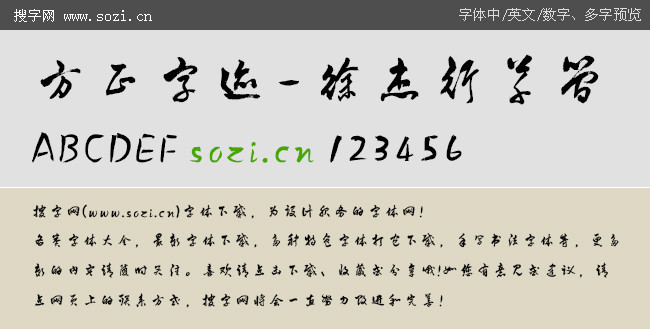
方正字跡-徐杰行草簡
搜字網(wǎng)提供一款方正字跡-徐杰行草簡中文字體下載,方正字跡-徐杰行草字體輕舞飛揚(yáng),而且連貫特殊,能夠適用于藝術(shù)設(shè)計(jì)、包裝印刷、簽名設(shè)計(jì)、圖形設(shè)計(jì)等領(lǐng)域。同時(shí)也是在市場上非常受歡迎的適合練習(xí)書法的字體。